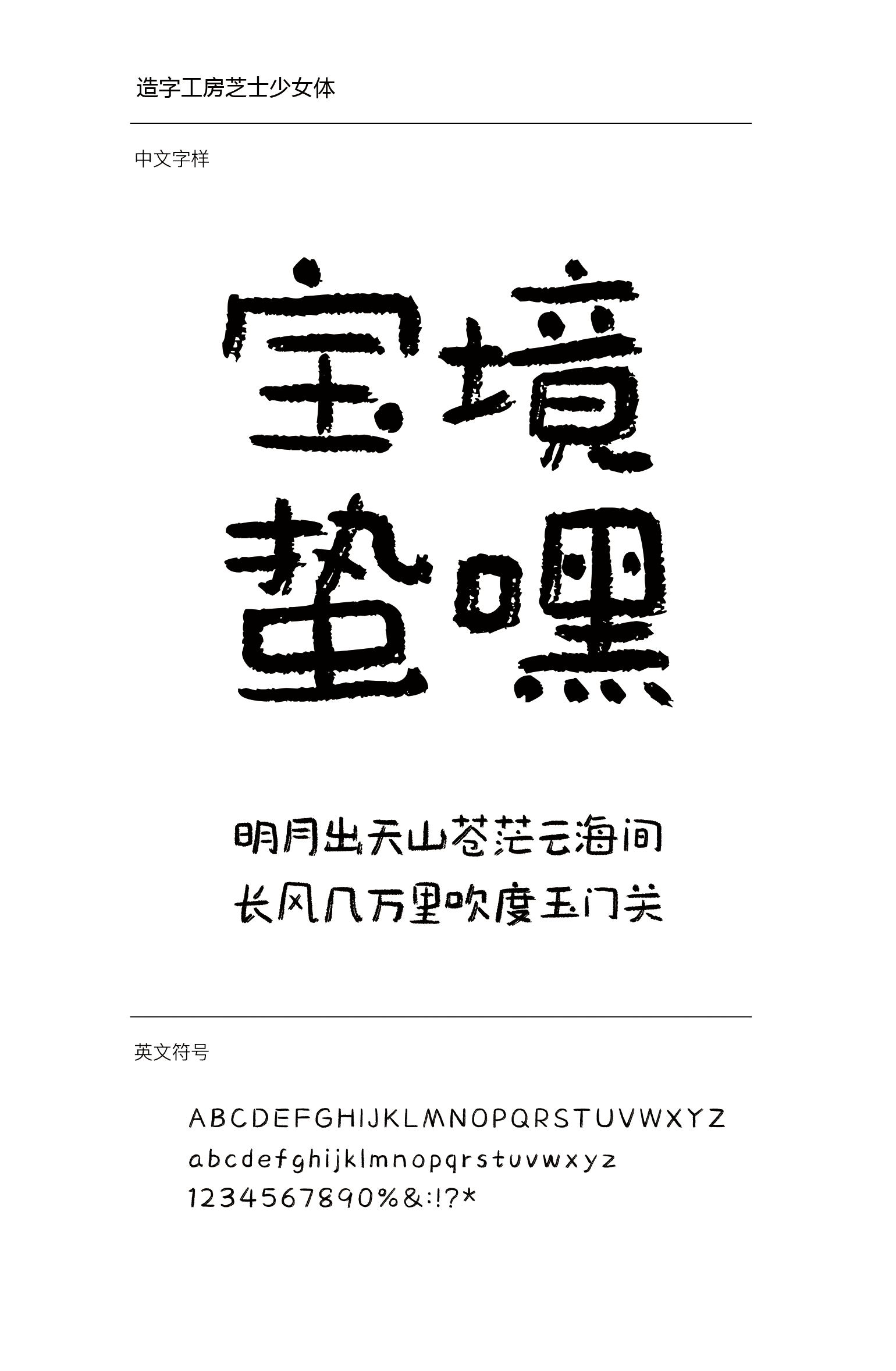
造字工房芝士少女
造字工房芝士少女设计说明
造字工房芝士少女体,字体形散神聚,趣味十足 ,字形结构不循章法,自然随意,笔法的独特纹理使字体风格稚拙灵动的同时不失质感,适用于儿童读物、艺术作品、广告设计、个性品牌设计,等视觉环境。本字体为简体字库,采用OpenType/CID格式,Adobe-GB1-5编码。基于中华人民共和国GB2312-80字符集标准,另按需添加101个汉字。共收容字数6864CJK汉字,ASCII常用字符100个。